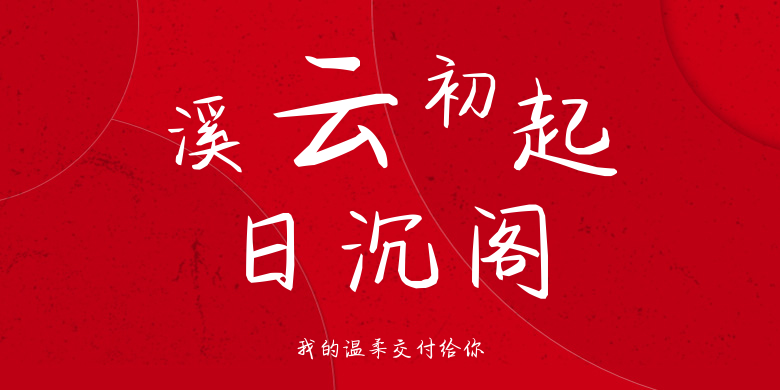
我的温柔交付给你
我的温柔交付给你,这款字体结构工整、笔画清晰,兼顾美观与易读性,适用于标题、正文、海报、包装、LOGO 等多种场景。字形优雅稳定,风格百搭耐看,适配日常排版与创意设计,让文字呈现更舒适、更具质感。我的温柔交付给你一笔一画,皆是细节,以均衡的比例、流畅的线条打造舒适视觉体验,字形端正大气,风格简约现代。无论是商业设计、品牌宣传还是日常排版,都能轻松驾驭,让文字更有格调与力量。我的温柔交付给你字体下载。